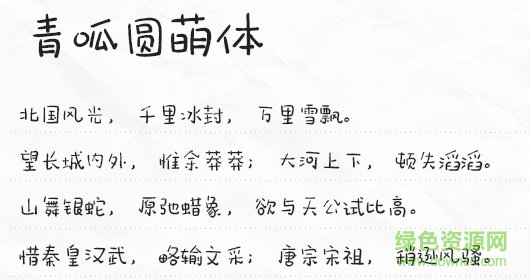
青呱圓萌字體
青呱圓萌體是一款十分q萌可愛的卡通字體,造型圓潤(rùn)而活潑,讓人體驗(yàn)生動(dòng)有趣的視覺呈現(xiàn),喜歡的朋友千萬(wàn)不要錯(cuò)過(guò),快來(lái)綠色資源網(wǎng)試試吧!
青呱圓萌字體特色
青呱圓萌體造型小巧而有趣,風(fēng)格上有著手寫字體的恣意和簡(jiǎn)約,結(jié)構(gòu)完整,沒有中規(guī)中矩的嚴(yán)肅,自稱一派,給大家的平面設(shè)計(jì)、藝術(shù)設(shè)計(jì)帶來(lái)更多悅目體驗(yàn)!